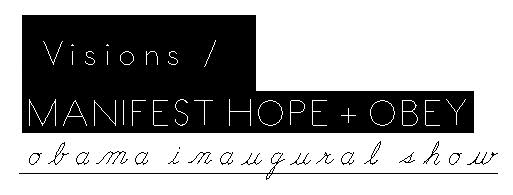
"non-type" schriftart
meine frage bezieht sich auf die "haus"-schriftart von non-type.
ich hab in letzter zeit öfters solche sehr dünnen, irgendwie pixelig wirkenden schriftarten auf internetseiten und so gesehen.
kann mir jemand sagen, wie sich diese oder ähnliche schriftarten nennen?
bitte entschuldigt meine mehr als dilettantische ausdrucksweise. ich kenn mich auf dem gebiet typografie nur sehr mäßig aus.
also für mich ist das die futura light und das schreckliche pixeln ist versehen bzw, unvermögen beim erstellen der web-gifs.
oder sollte das absicht sein? :shock:
vielen dank. wobei ich zweifel habe, dass das futura ist. bei futura sind doch glaub ich die äußeren M-balken eher ein bisschen schräg, wohingegen die hier komplett gerade sind. und bei futura sind auch alle waagerechten E-balken gleich lang. aber ich bin mir auch nicht sicher...
und zu dem pixeligen. also ich bin davon ausgegangen, dass es absicht ist. die generelle aufmachung der seite is ja eher ein bisschen pixelig.
vielleicht kann mir ja jemand kurz sagen, wie man diesen effekt künstlich erreichen könnte (oder mich irgendwohin verweisen, wo ich mit der frage richtig bin)? ich würde diesen effekt gern mit photoshop für eine illustration vewenden und habe schon diverse dinge ausprobiert, bin aber leider nie zu einem befriedigenden ergebnis gekommen.
Du könntest nach ähnlichen Pixel- bzw. Bitmapfonts suchen. Die gibt es auf Freefontseiten wie Sand am Meer. Besonders bei Fontstruckt kann sich ein Blick lohnen, dort könntest Du nötigenfalls auch relativ leicht die Schrift nachbauen.
Alternativkönntst Du die Ränder im Grafikprogramm Deiner Wahl übermäßig schärfen und dann als schwarz-weiße Grafik speicher. Natürlich könntest Du auch ein Grafikprogramm benutzen, das mühelos ganz von allein Schriften so Pixelig rendert: MS Paint. :rockon:
ich werd mir auf jeden fall mal das mit dem pixel- bzw bitmap-fonts angucken.
Stattdessen doch lieber einfach die Kantenglättung der Schrift ausschalten:
...oder hab ich da was falsch verstanden?